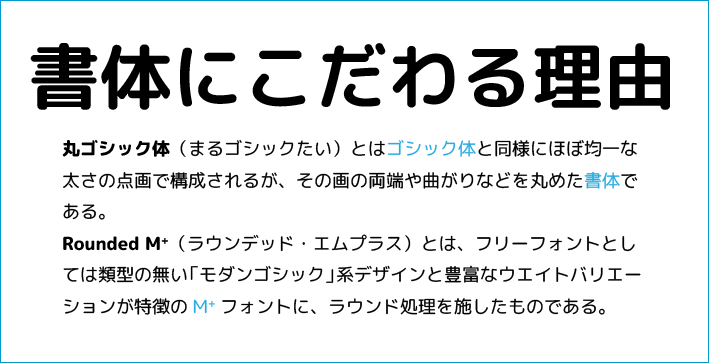
フリーフォントM+を丸ゴシック化したRounded M+
日本語フォント「M+」の丸ゴシック体が出てます。
Rounded M+(ラウンデッド・エムプラス)という名前です。
ひらがななどかわいらしくてロゴにも良いと思います。
プロポーショナル(可変幅)
Rounded M+ 1p、Rounded M+ 2p、Rounded M+ 1c、Rounded M+ 2c
等幅(モノスペース)
Rounded M+ 1m、Rounded M+ 2m、Rounded M+ 1mn
紹介
• すべての文字に対して丸ゴシック処理をしてあります。なので、□★などの記号も角が丸いです。欧米文字もすべてラウンデッドです。
制限事項
• このフォントの含む文字は M+ TESTFLIGHT 046+2012-02-24朝までの追加分、つまり約3775文字です。JIS第1、第2水準の6355文字には足りないので、表示されない漢字があります。
• 縦書きは等幅フォント(1m, 2m, 1mn)のみ可能です。より正確に言うとAdobe製品ではプロポーショナルフォント(1p, 2p, 1c, 2c)が縦書き文字になりません(Illustrator CS4で確認)。